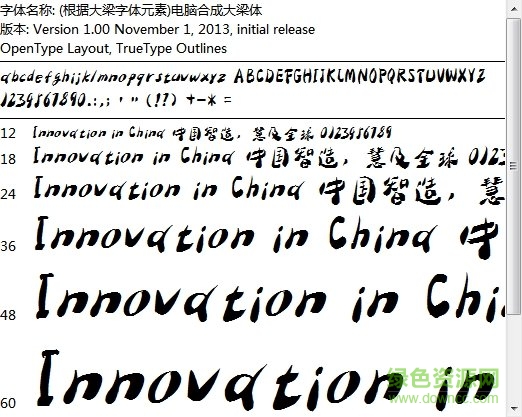
電腦合成大梁體字庫
電腦合成大梁體是自一款由電腦生成的古文字體,通過對古文進(jìn)行拓印,更好的保留遠(yuǎn)古文字的造型和結(jié)構(gòu),更好的傳承中國古代文字,綠色資源網(wǎng)獨(dú)家推薦!
電腦合成大梁體介紹
全世界第一套由電腦生成的漢字毛筆字字庫---大梁體毛筆書法字庫問世,該套字庫是依據(jù)大梁藝術(shù)館館長、著名書法家大梁的書法字體風(fēng)格、用筆特點(diǎn),篩檢提煉出“大梁字體元素”,由電腦自動生成。該項(xiàng)目由“湖南羅西字庫制作全國聯(lián)盟”拆組合成制作完工。
字體特色
該套字庫完全是按照國家語言文字工作委員會的專業(yè)要求,成功地生成了我們國家常規(guī)使用的6763個純毛筆書法字,并安裝成能夠廣泛使用的TTF格式字庫。該套字庫的字體結(jié)構(gòu)基本符合大梁老師的書法理念,基本保持了“大梁體”的書法風(fēng)格和完美度,且增強(qiáng)了統(tǒng)一性、和諧感。
大梁體毛筆書法字庫問世,解決了如何利用計算機(jī)自動拆分這些作品的自然筆畫,并準(zhǔn)確地還原他們的風(fēng)格,不僅可以加快字庫制作進(jìn)程,對于傳承中華文明也有重要意義。